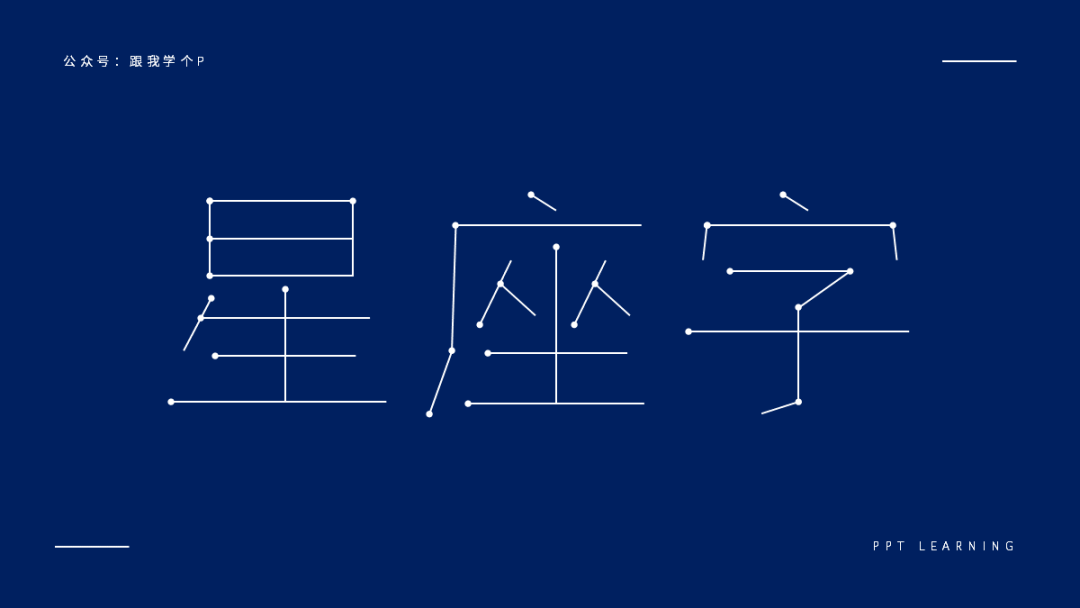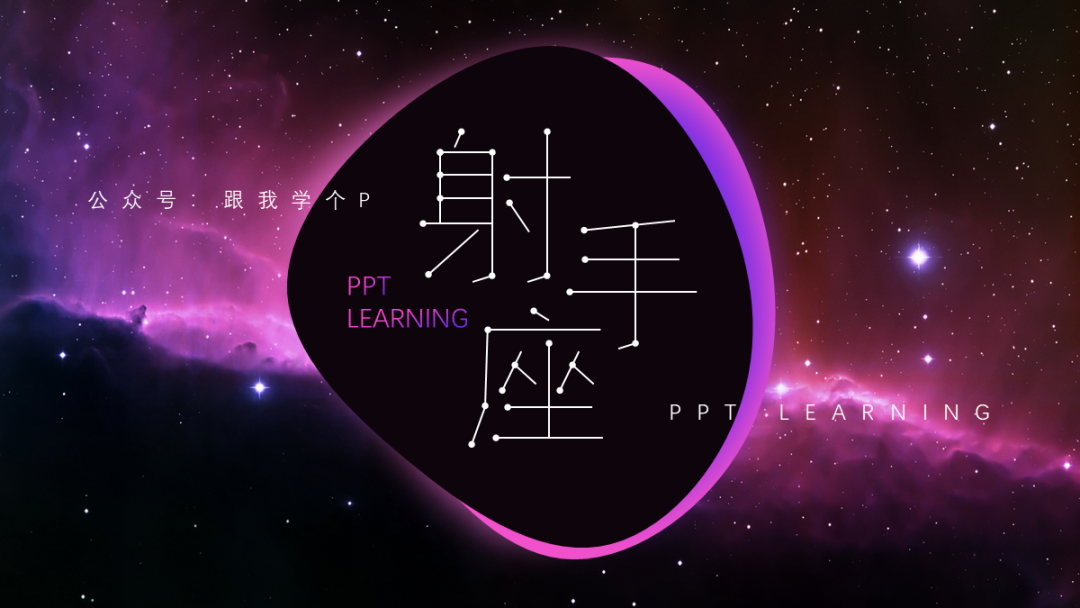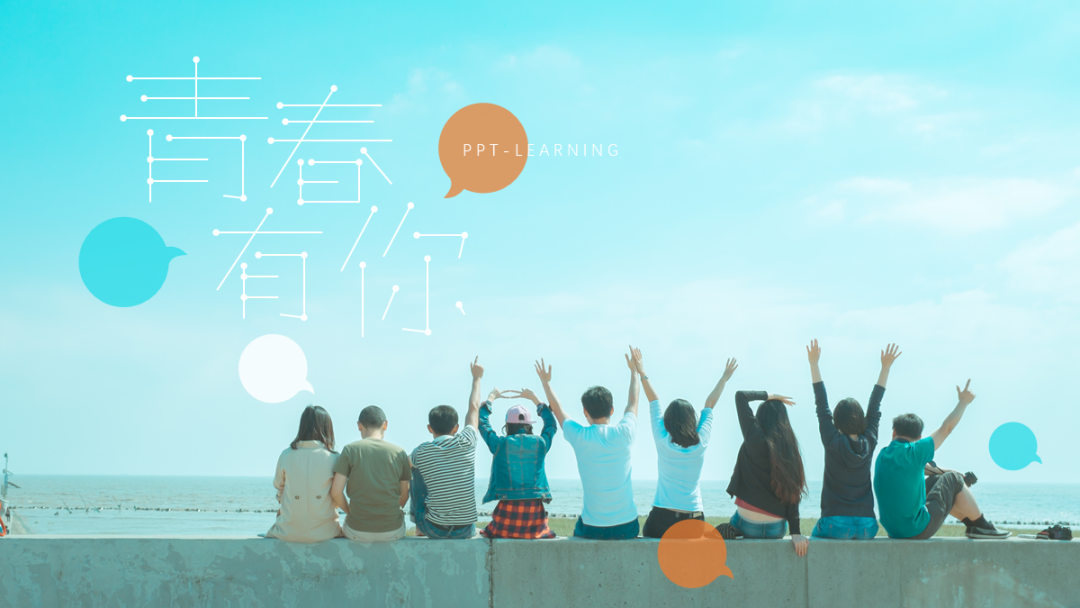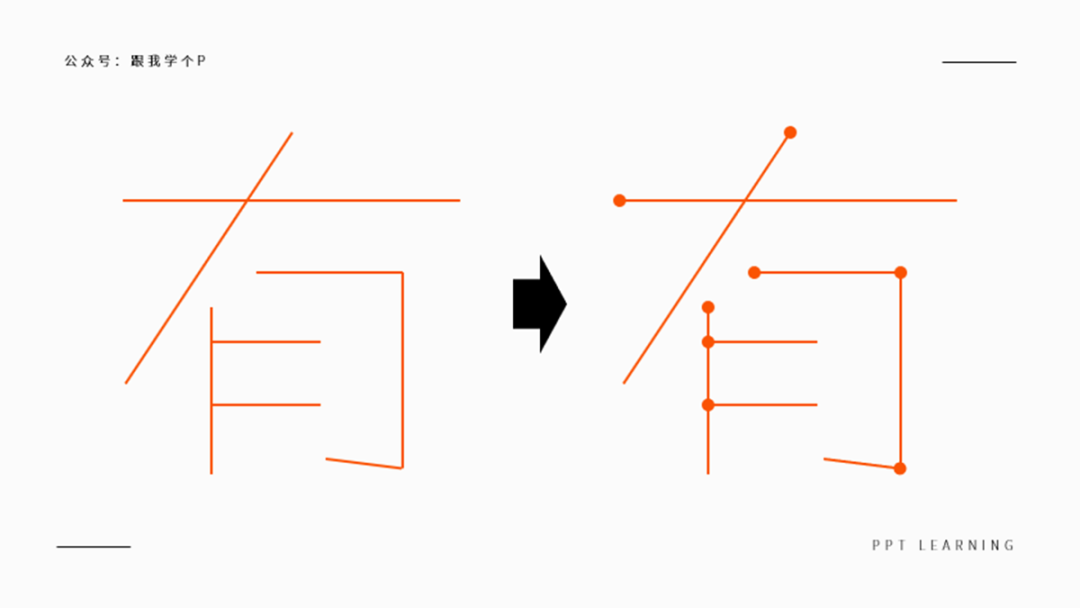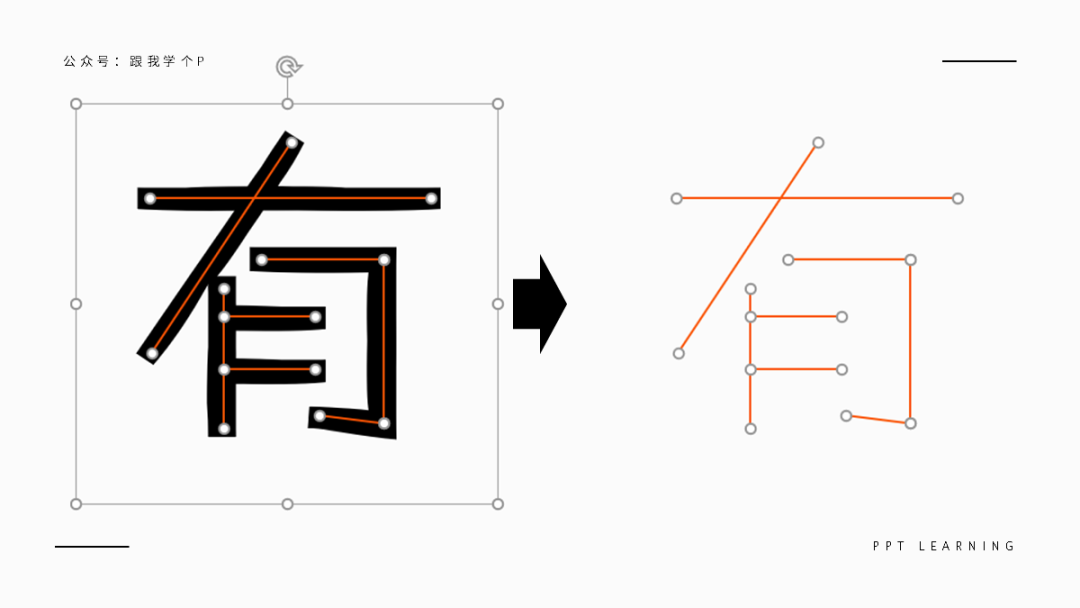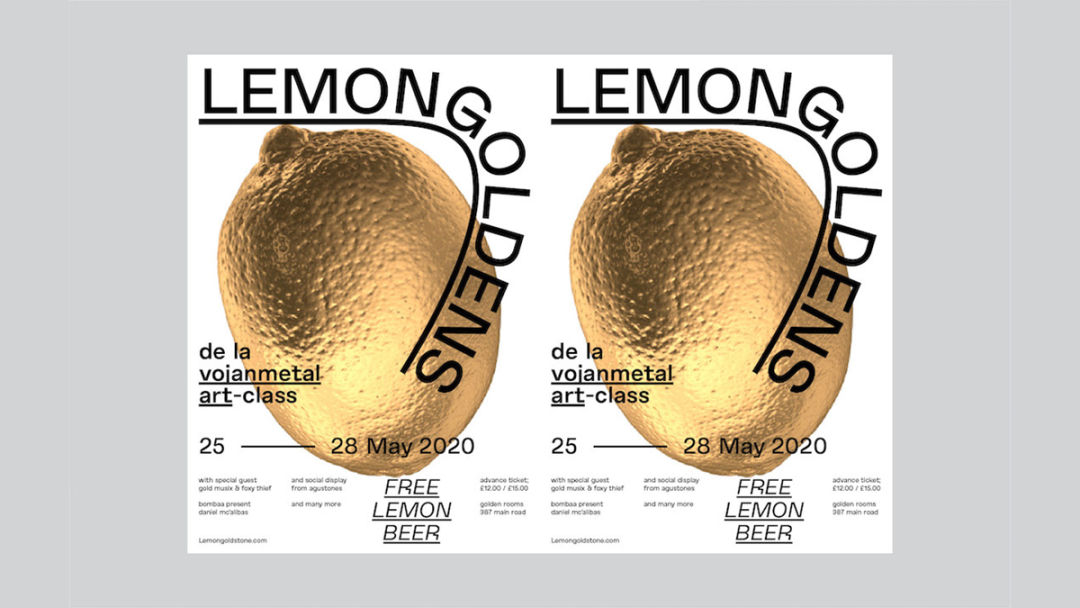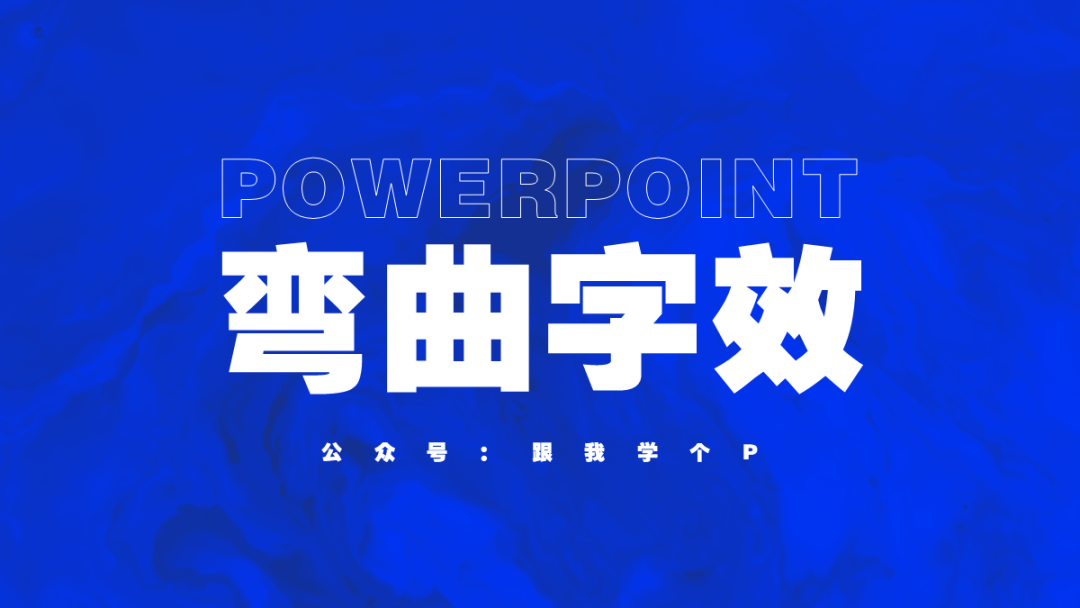
学会这四种字效,甲方再不会说我画面单调了
假期后第一天,是不是还没回过神来,那今天柚子就上一篇PPT字效的干货, 保准你醒得一机灵~
一说起星座,大概就会想起下面的图案,点和线连在一起。除了可以用在星空风格的PPT中,一些比较文艺的画面,它也很适合。
1)插入文字,沿着文字的笔画放置线条,接着删掉文字,只留下线条;2)选中所有线条,再随便右击一根线条,点击【设置形状格式】-【填充】-【线条】-将【开始箭头类型】设置为【圆形箭头】:ps.这笔画越看越像火柴,为啥不叫火柴字,因为字由上有一款,你可以对比看看~1)正常插入文字,在选中文本框的状态下,点击界面右上角的【形状格式】-【文本效果】-【转换】-选择【拱形】类型:2)拉动小黄点,或是调整边框的大小,都可以修改文字的弯曲程度:另外有时间的话,你可以去鼓捣一下【转换】里面的文字变形,会有惊喜哦~1)先插入文字,接着在文字上方盖上多个细长细长细长……的矩形:2)同时框选中文字以及所有的矩形,点击【形状格式】-【合并形状】-【拆分】:
然后神奇的事情就发生了,你会看到文字被拆得七零八落,连它妈都不认识了:3)删掉那些被拆出来的零碎形状,稍微移动一下碎片的位置,就大功告成了~多说一句,字由上有一款免费商用的西文字体Bisect,都直接给你错好位了。上面介绍的三种字效,都需要你费一点秀发才能做出来,但是像下面这种,只需要一秒钟……